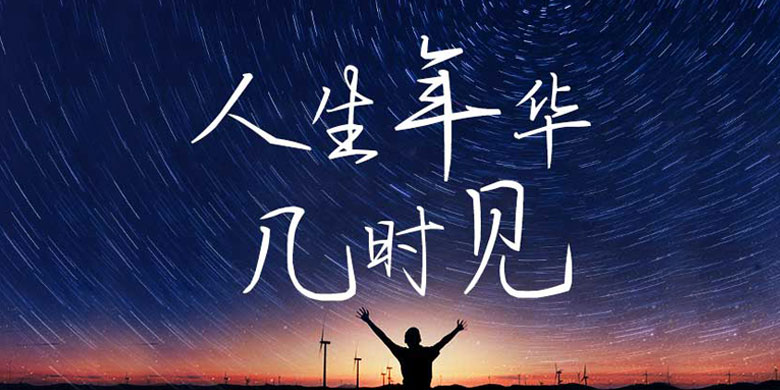
方正手迹-人生年华几时见
方正手迹-人生年华几时见,这款字体结构工整、笔画清晰,兼顾美观与易读性,适用于标题、正文、海报、包装、LOGO 等多种场景。字形优雅稳定,风格百搭耐看,适配日常排版与创意设计,让文字呈现更舒适、更具质感。方正手迹-人生年华几时见一笔一画,皆是细节,以均衡的比例、流畅的线条打造舒适视觉体验,字形端正大气,风格简约现代。无论是商业设计、品牌宣传还是日常排版,都能轻松驾驭,让文字更有格调与力量。方正手迹-人生年华几时见字体下载。
字体品牌: 方正手迹 设计师:余丹 字体分类:常规书写·硬笔 字体属性:精品字 字符集:大陆简体(GB2312-80) 发布时间: 2020
这款字体笔法细腻,结构严谨,一点一画间才情横溢,韵味悠长极具内涵,整体呈右上趋势。适用于现代诗歌、短文的排版以及文化、商业类品牌的广告语设计。